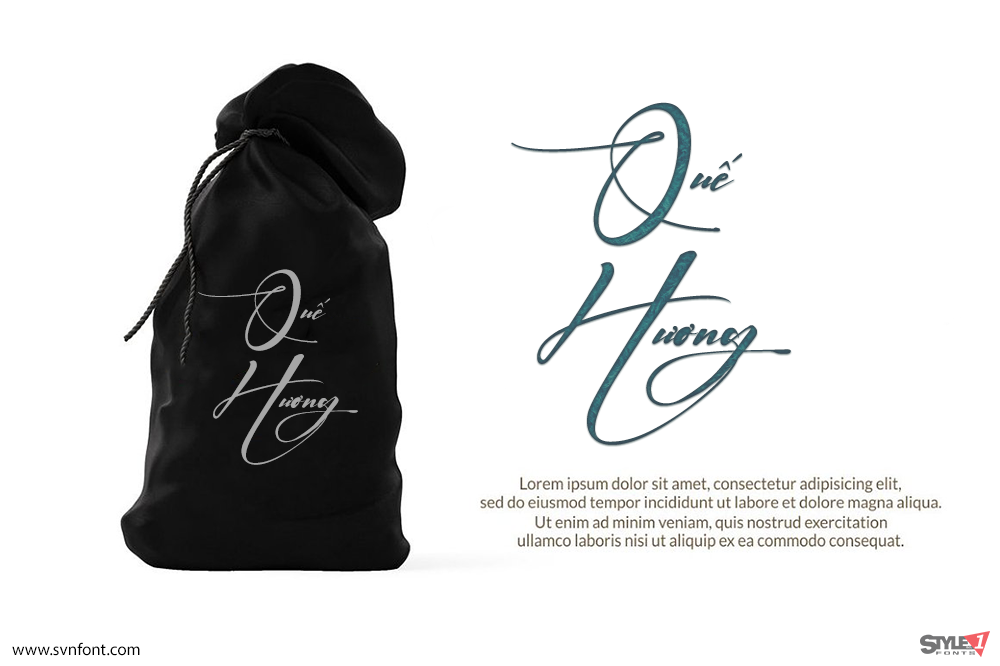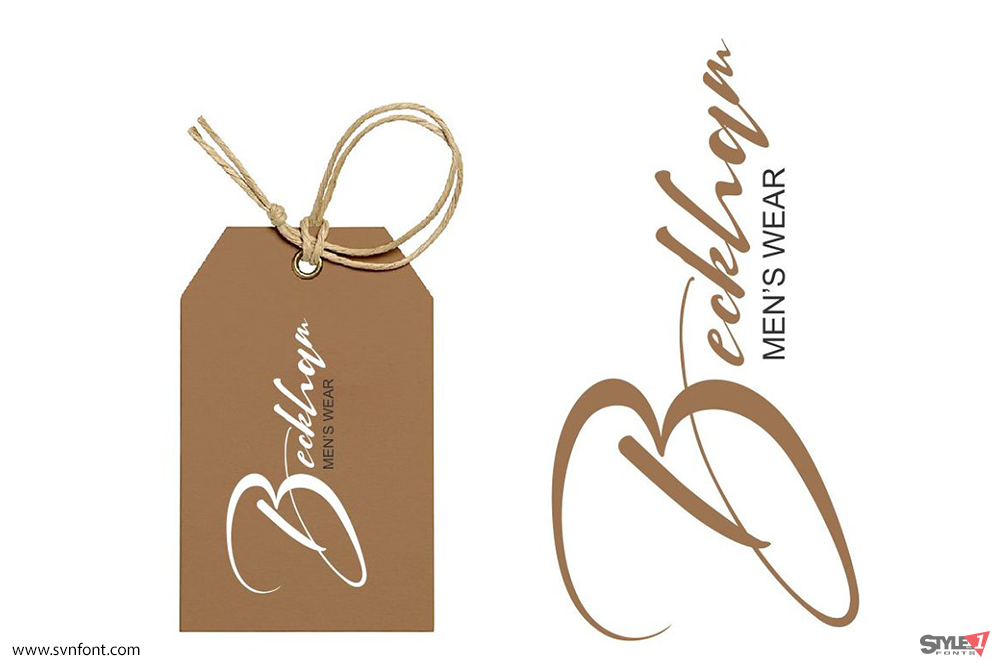
Giới thiệu font chữ ký Signatrue. Đây là lựa chọn hoàn hảo để tạo logo chữ ký và watermark cho studio nhiếp ảnh hoặc thương hiệu cá nhân, đặc biệt phù hợp cho logo dạng chữ ký hoặc chữ cái viết tắt.
Font được thiết kế với tinh thần thanh lịch, chuyên nghiệp và độc đáo. Bạn có thể dùng thử ngay chỉ bằng cách gõ tên mong muốn — mọi thứ được tối giản trong thao tác nhưng vẫn mang vẻ sang trọng và cao cấp.
Font có biến thể chữ thường (lowercase alternate) rất giống nét viết tay bằng bút, nên cực kỳ phù hợp cho chữ ký, logo, watermark ảnh và nhiều ứng dụng khác. Chỉ cần viết, bạn đã có thể tạo chữ ký cá nhân hóa hoặc logo chữ ký riêng cho mình.
Đây là một font chữ ký ấn tượng dành cho tất cả mọi người.